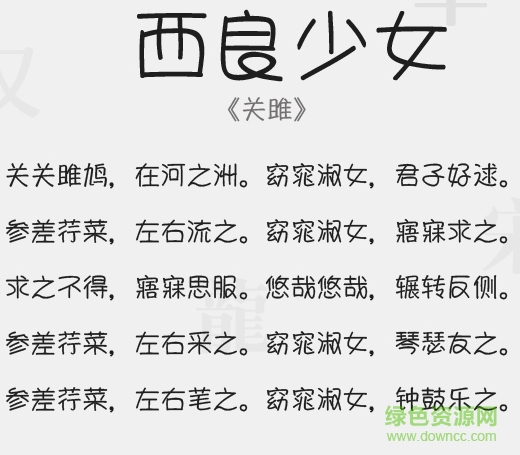
西良少女字體是一款很生動(dòng)活潑的藝術(shù)字體,有著如少女版姣好的姿態(tài),適合各種海報(bào)設(shè)計(jì)、藝術(shù)創(chuàng)作、排版設(shè)計(jì)等,快來(lái)綠色資源網(wǎng)下載看看吧!
字體簡(jiǎn)介西良少女字體是一款用于平面設(shè)計(jì)方面的字體,支持中英文輸入,非常有古風(fēng)感。